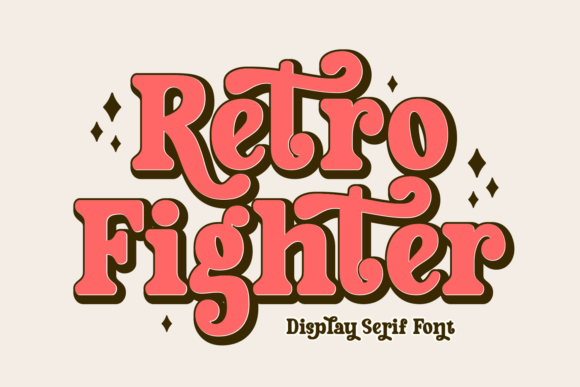
Retro Fighter
Retro Fighter – A Fonte que Transforma Qualquer Projeto em Uma Viagem no Tempo
Se você está procurando a combinação perfeita entre estilo retrô e modernidade refinada, a família tipográfica Retro Fighter é a escolha certeira. Cada letra foi desenhada à mão, trazendo um charme artesanal que se destaca tanto em telas digitais quanto em impressões de alta qualidade.
- Design vintage autêntico: inspirada nos clássicos dos anos 70‑80, a fonte oferece traços que lembram letreiros de arcade e cartazes de cinema antigo.
- Versatilidade de uso: ideal para posts de redes sociais, legendas de fotos, projetos escolares, convites, cartões de felicitações e revistas glossy.
- Suporte multilíngue: cobre uma ampla gama de caracteres, garantindo ótima legibilidade em diferentes idiomas.
- Alta legibilidade: estrutura limpa e simples que mantém a nitidez tanto em tamanhos pequenos quanto em grandes formatos de impressão.
Por que Retro Fighter é a Melhor Opção para Seu Projeto?
Além da estética marcante, a Retro Fighter traz à tona uma sensação de nostalgia que cativa o público‑alvo, aumentando o engajamento em campanhas de marketing e reforçando a identidade visual de marcas que desejam se destacar. Seu acabamento artesanal confere exclusividade, enquanto a clareza tipográfica assegura que a mensagem seja transmitida de forma impactante.
Em resumo, Retro Fighter não é apenas mais uma fonte retro; é uma ferramenta poderosa que eleva qualquer projeto ao status de obra‑de‑arte visual. Seja para dar vida a um post nas redes sociais ou para imprimir capas de revistas com qualidade premium, a Retro Fighter entrega visual vintage, legibilidade impecável e charme artesanal em um único pacote.